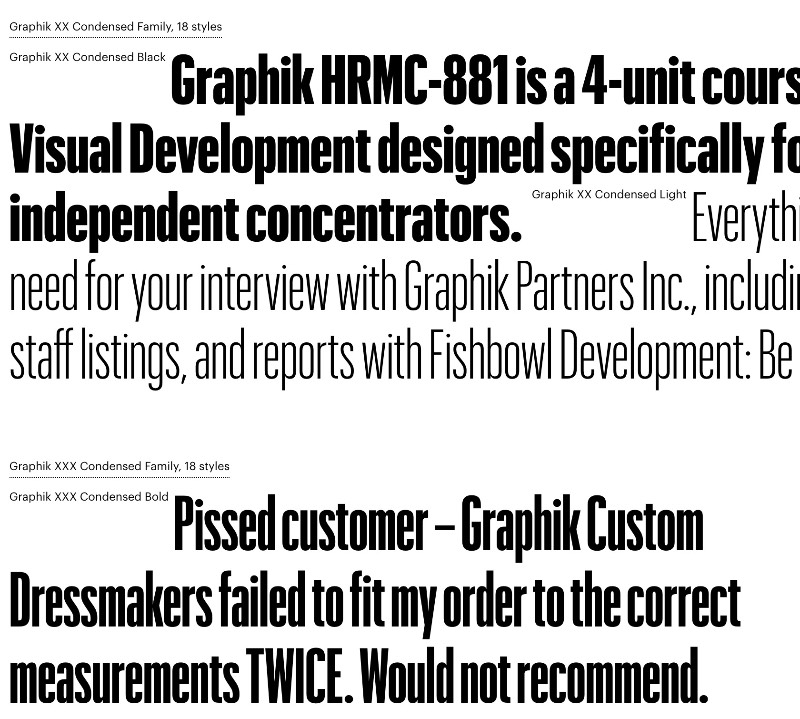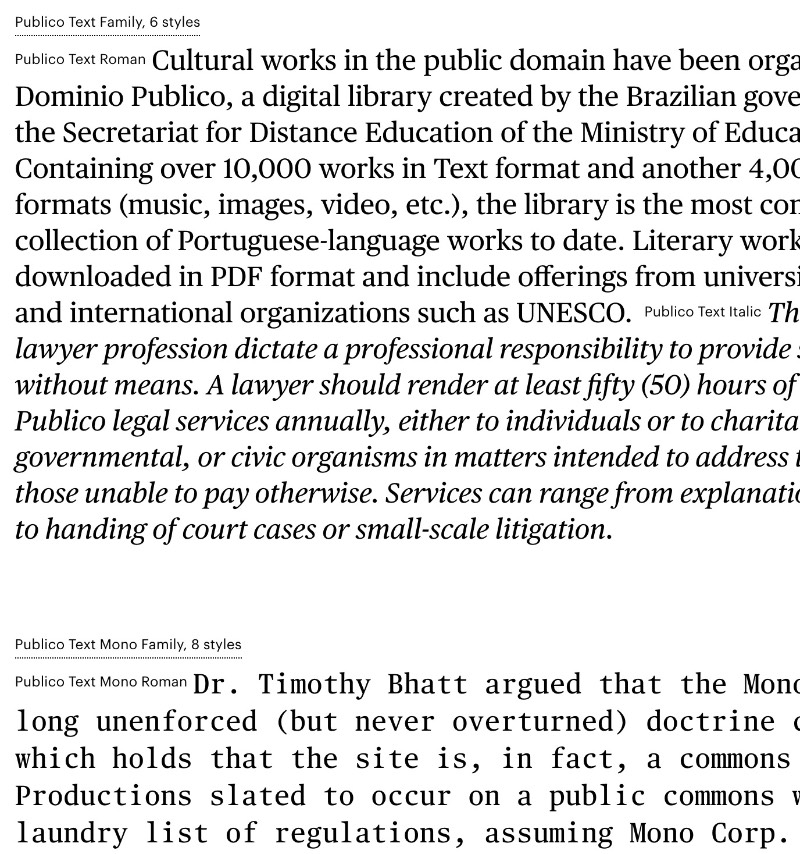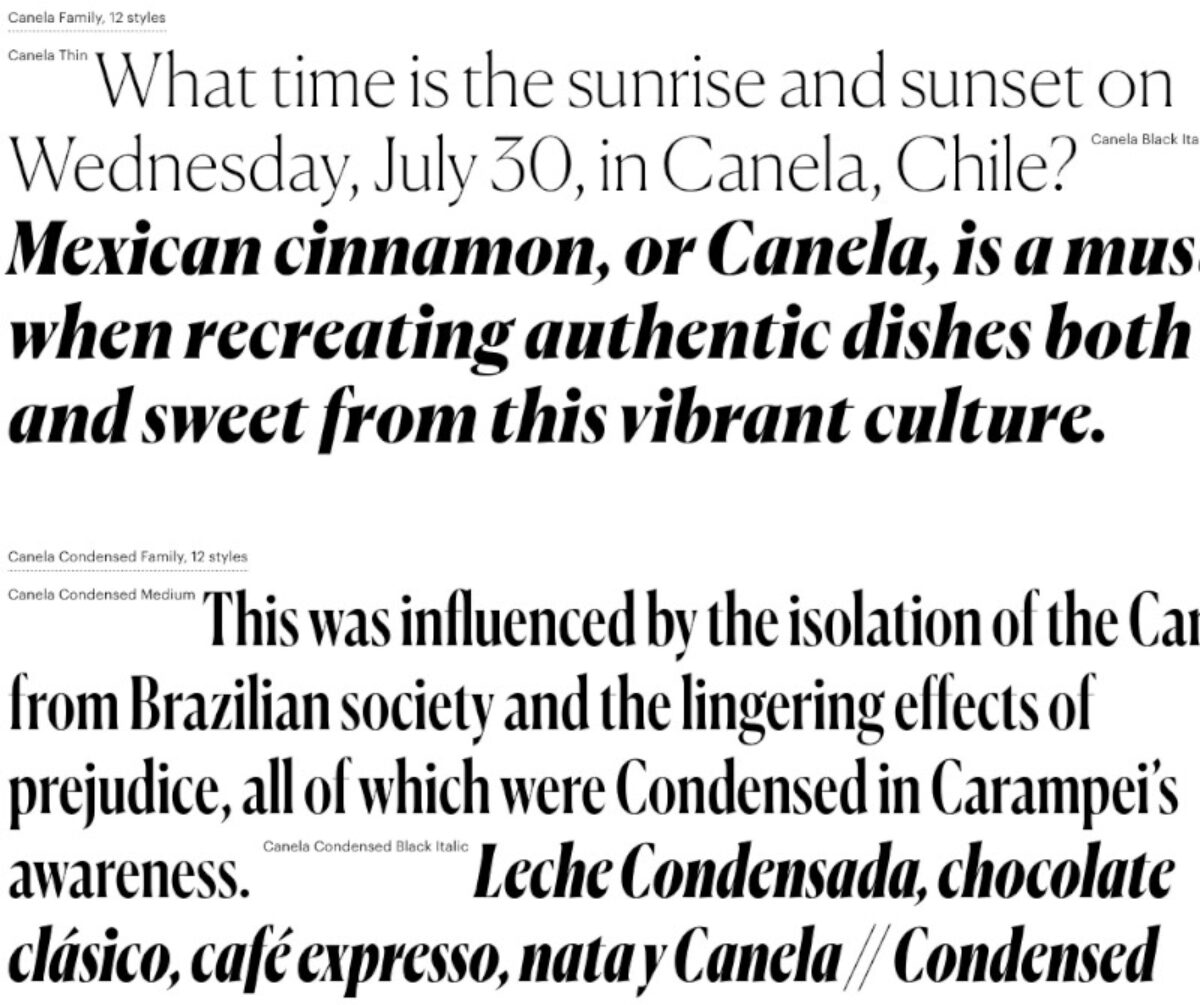
As incríveis fontes gratuitas do Mac OS Catalina que você não sabia que tinha acesso
Recentemente, a Apple andou licenciando fontes de type foundries como Mark Simonson Studio, Commercial Type, Klim Type Foundry, e essas fontes gratuitas estão disponíveis como fontes de sistema no Mac OS Catalina. Porém, elas fazem parte de um download opcional e muitos usuários não sabem que tem acesso a isso.
Por isso mesmo que aqui estou eu escrevendo esse artigo para informar todos usuários do Mac OS Catalina que vocês tem acesso a uma belíssima coleção de fontes gratuitas.
Se você explorar o Fontbook, vai se deparar com inúmeras fontes gratuitas para download mas, muitas delas, são não-latinas e muito provavelmente você não vai chegar a usá-las.
Entre as latinas, as que eu achei mais interessante foram as abaixo.
Canela do Commercial Type. Essa fonte vem com um tipo de letra gracioso que desafia muitas das classificações tradicionais. Desenhado por Miguel Reyes, suas formas estão em um espaço ambíguo entre sans e serif, macio e nítido, moderno, mas com raízes no clássico. Founders Grotesk do Klim Type Foundry que é uma fusão contemporânea de formas grotescas clássicos.
Graphik da Commercial Type que foi originalmente lançada em 2009 e já se tornou um clássico moderno. Com uma grade racional composta por nove pesos em oito larguras diferentes, a Graphik é criada para máxima flexibilidade na comunicação. Proxima Nova do Mark Simonson Studio que preenche a lacuna entre tipos de letra como Futura e Akzidenz Grotesk. O resultado é um híbrido que combina proporções modernas com uma aparência geométrica. Inicialmente lançada em 1994 como Proxima Sans, essa fonte foi expandida para o que pode ser visto hoje.